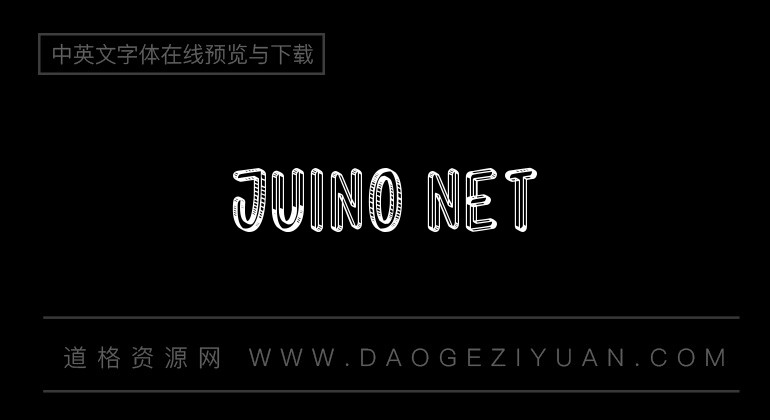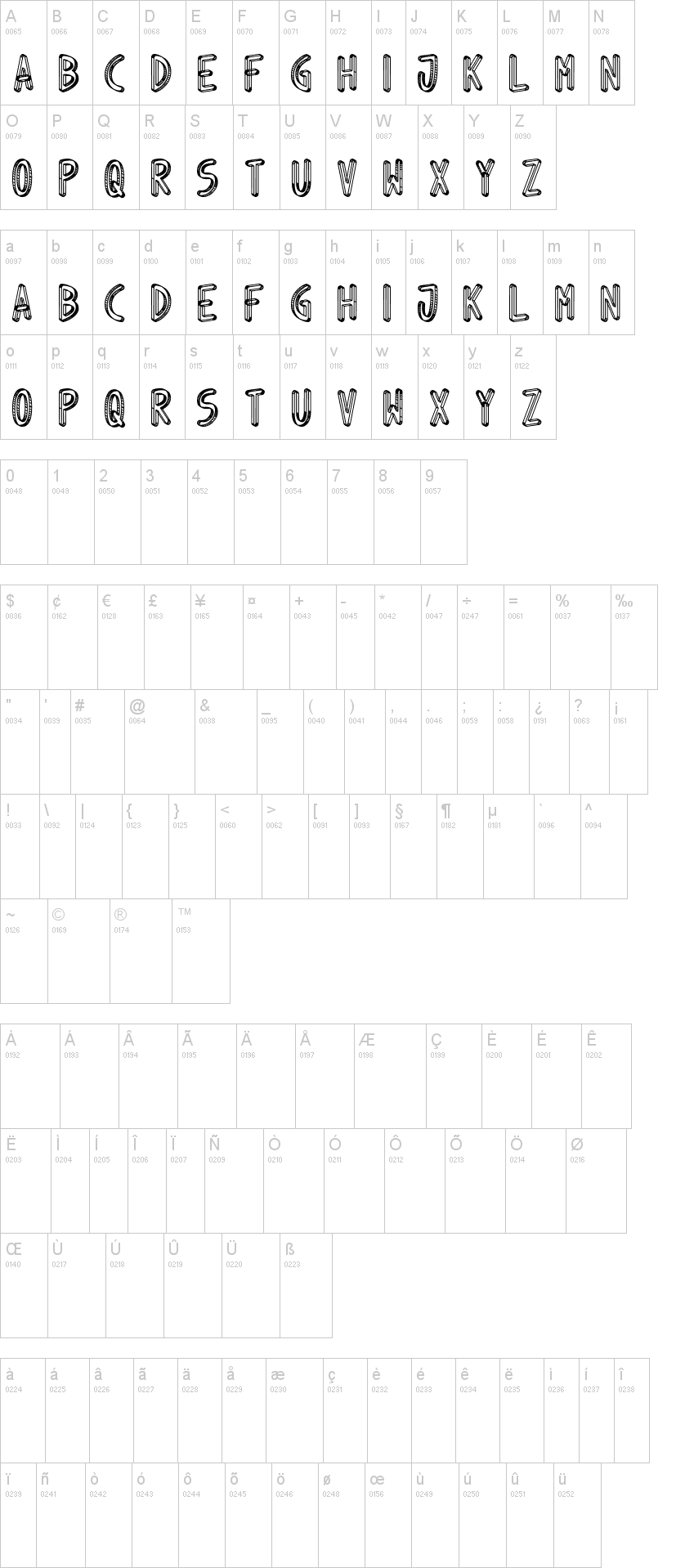
Juino Net 字体是一款免费的开源字体,由 Juino 团队设计和开发。Juino Net 字体具有几何结构,细节精细,具有良好的可读性,适合用于多种用途,包括网页设计、桌面出版、平面设计、标志设计等。Juino Net 字体支持多种字符集,具有拉丁字母、希腊字母、俄文字母、西里尔字母等特性,可以满足不同的语言需求。内容介绍
Juino Net是一款非常不错的手写艺术字体,具有很好的视觉感,适合于文化类的宣传设计、商业类品牌的广告和产品包装设计以及个性化文字排版等较多场景。